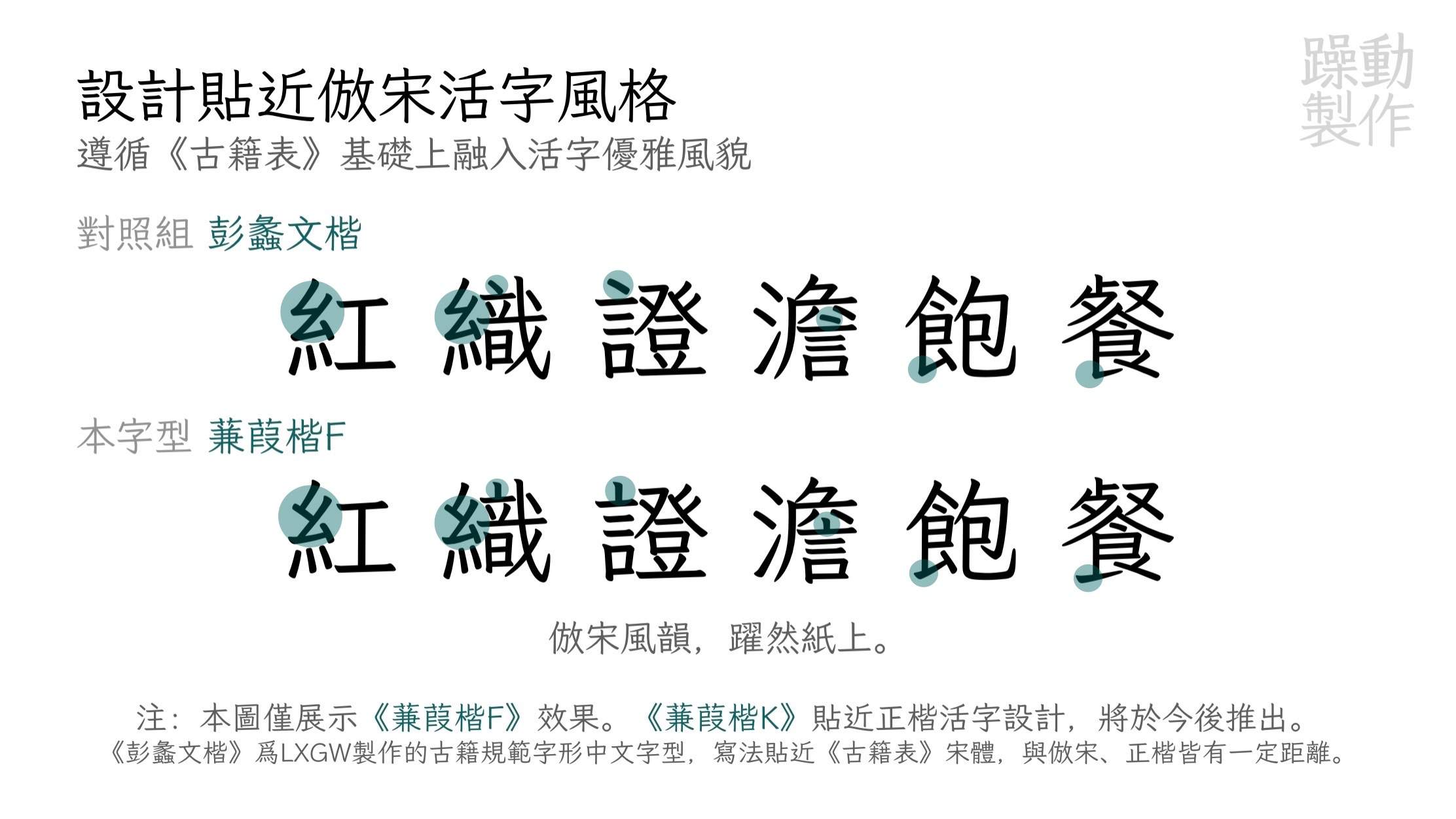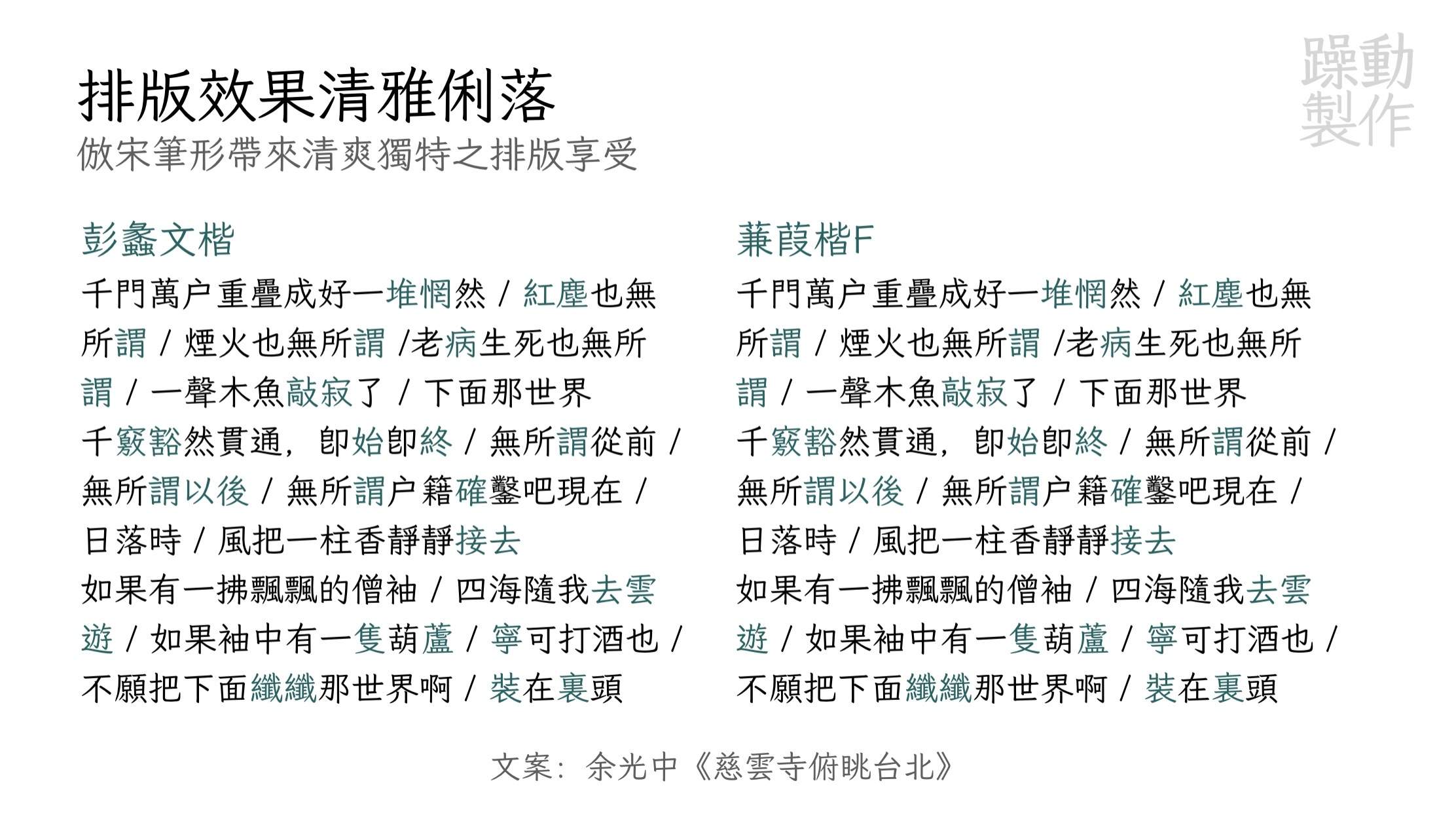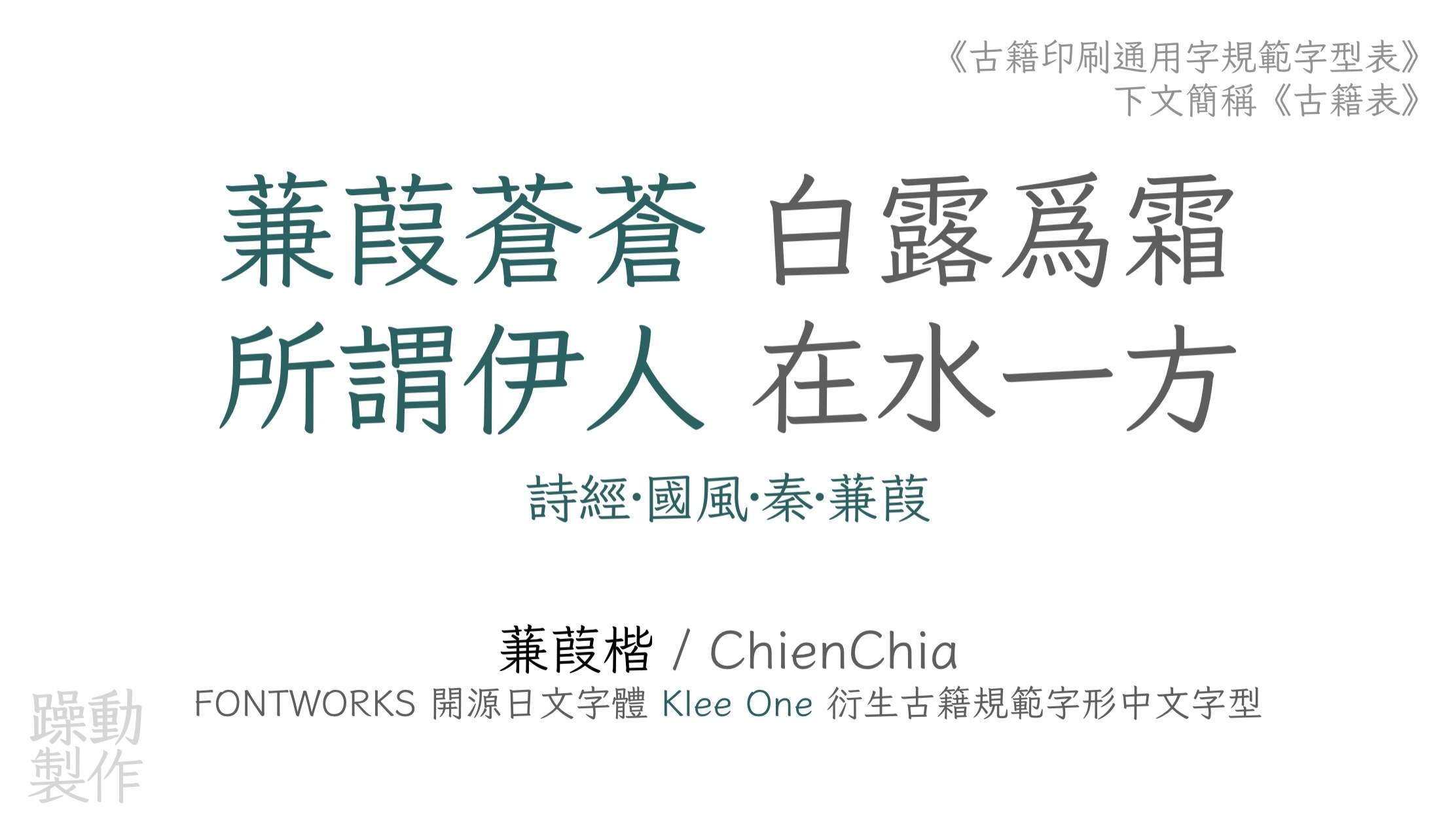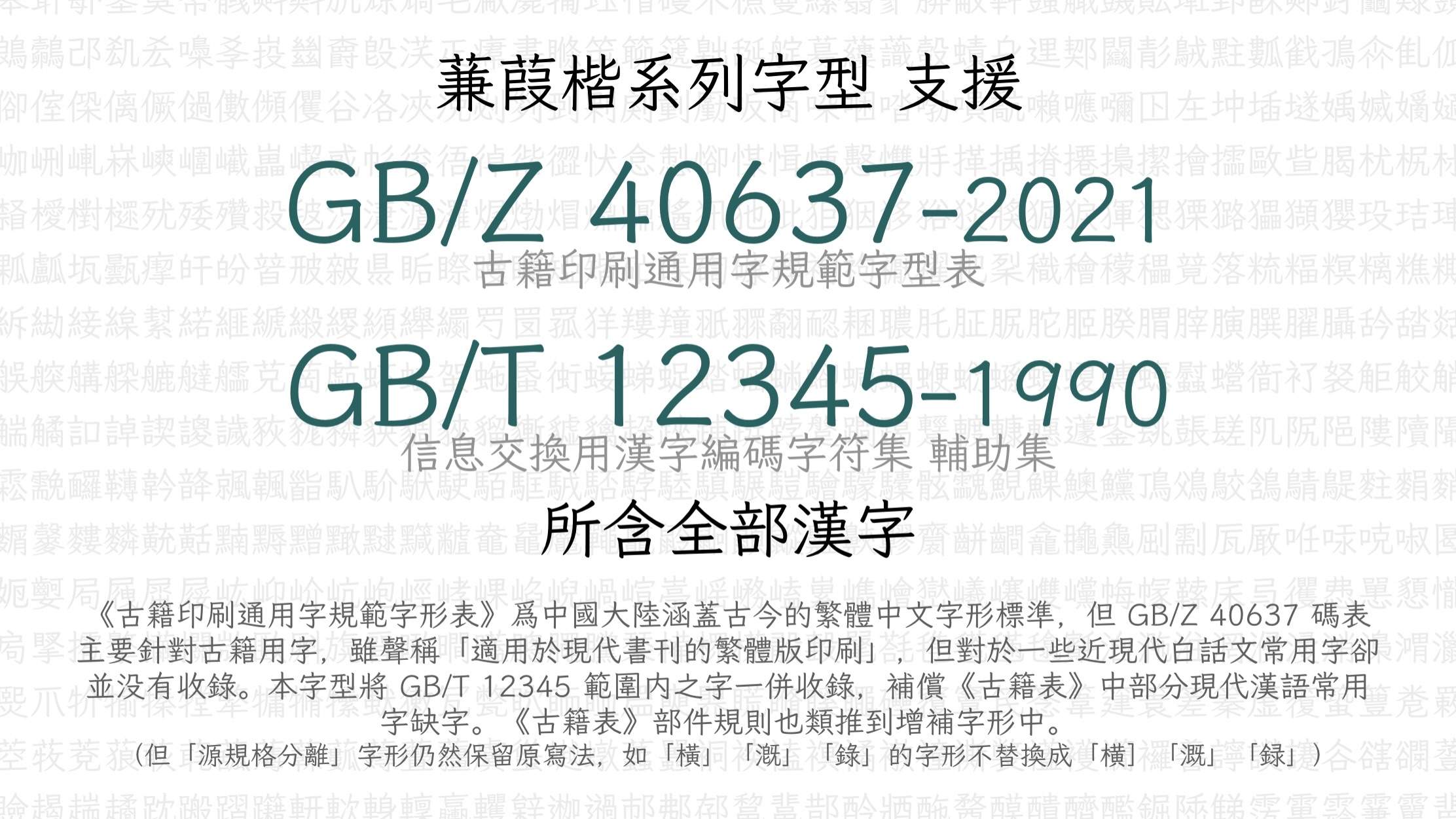
蒹葭楷/ ChienChia
基于 Klee One 字体衍生,参考《古籍印刷通用字规范字形表》(GB/Z 40637-2021)收字和调整字形的开源字体。
《蒹葭楷》是基于 Fontworks(现日本蒙纳株式会社,Monotype KK)所发布的开源字体 Klee One 的衍生字体,参考《古籍印刷通用字规范字形表》(GB/Z 40637-2021)收字和调整字形。
《古籍印刷通用字规范字形表》(GB/Z 40637-2021)是 1949 年以来中国大陆第一次对传世古籍印刷字的第一次整理规范,也是中国大陆第一部正式针对繁体字制定的字形规范。这部指导性技术文件声称「适用于传世古籍的印刷出版,以及现代书刊的繁体版印刷」,共收录了 14,250 个汉字字形,并提供每个字的首音和 ISO/IEC 10646 编码。其收录 GB/Z 40637-2021 范围内的全部汉字,参考 GB/Z 40637-2021 所规定的字形进行调整,并计划释出分别接近仿宋和正楷活字的设计的两个版本,现接近仿宋设计的《蒹葭楷 F》已开发完毕。但愿这一开源字体项目,能为《古籍印刷通用字规范字形表》颁布后的实践贡献一份绵薄之力,为古籍印刷字体提供一种新的选择。
• GB/Z 40637-2021 所收录的 14,250 个汉字,用于「传世古籍」所需汉字的排版与显示;
• GB/T 12345-1990 所收录的 6,866 个汉字,用于「现代书刊的繁体版本」所需汉字的排版与显示;
• Unicode 康熙部首区段所收录的 214 个部首字符,参考《康熙字典》总目中的部首字形进行取舍调整;
• 全半角 ASCII、拉丁补充-1 区、拉丁扩展 A 区、拉丁扩展 B 区、国际音标扩展区、拉丁附加扩展区、注音符号;
• 现代标点符号,以及古代汉语勾乙号「𖿢」、重文号「𖿣」;
• 易经、太玄经、算筹、中国象棋、中国传统圆形吉祥图案等符号;
葭楷字体展示,内容是诗经蒹葭里的诗句,由躁动制作,基于Klee One衍生,符合古籍印刷通用字规范。-刊刻Kntuk
《蒹葭楷F》字体设计贴近做宋活字风格,与《彭蠡文楷》对照展示“紅織證澹飽餐”,《蒹葭楷K》将于今后推出。-刊刻Kntuk
展示彭蠡文楷与蒹葭楷F宋笔形字体的排版效果,标题排版效果清雅俐落,文案为余光中《慈雲寺俯眺台北》-刊刻Kntuk
蒹葭楷系列字型支持GB/Z 40637-2021古籍印刷通用字规范字型表和GB/T 12345-1990信息交换用汉字编码字符集辅助集所含全部汉字,补偿现代常用字缺字,并保留源规格分离的原写法。-刊刻Kntuk